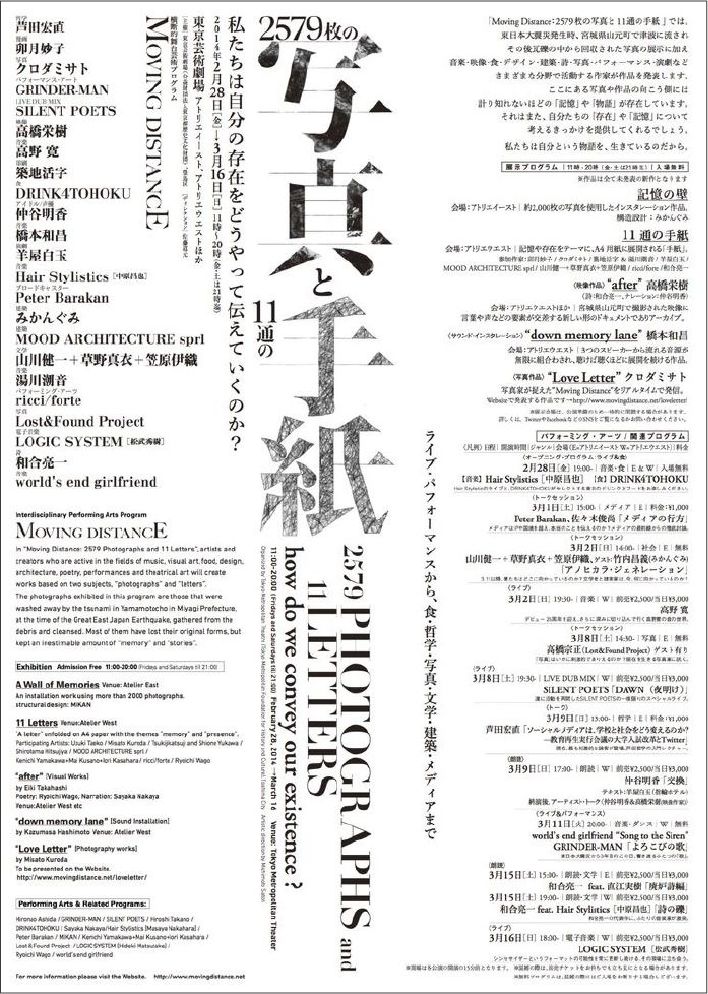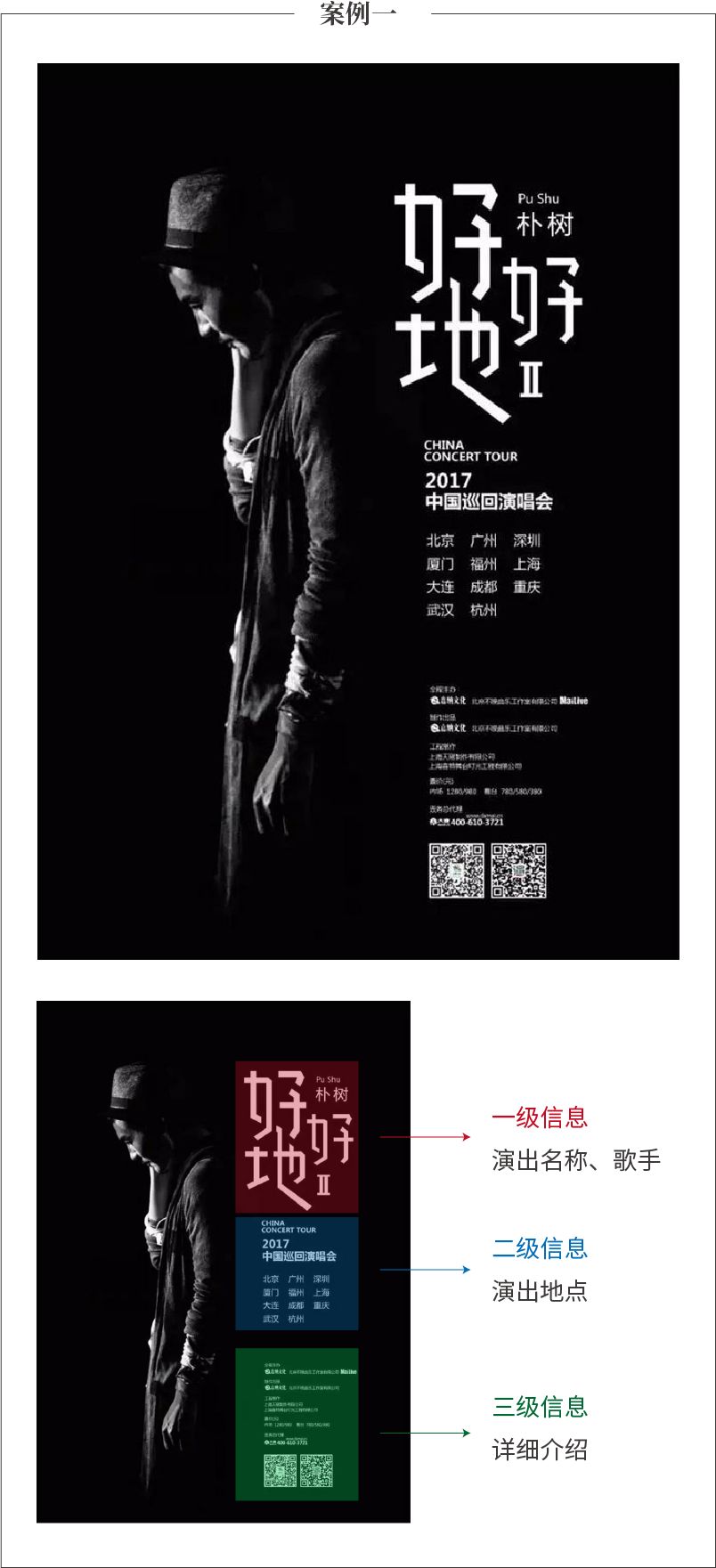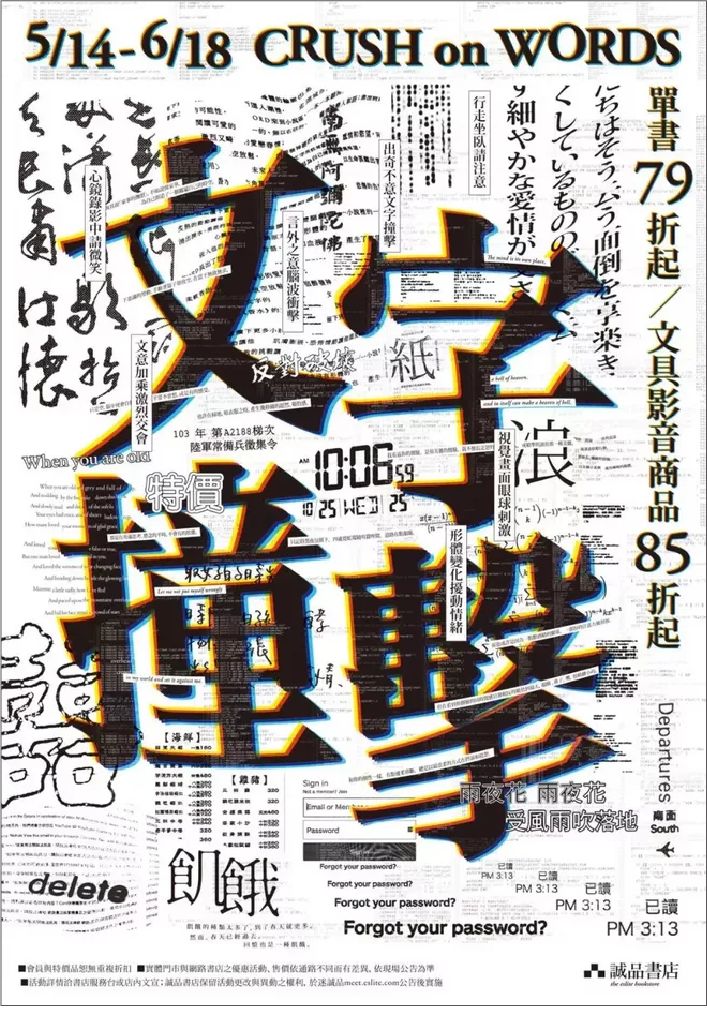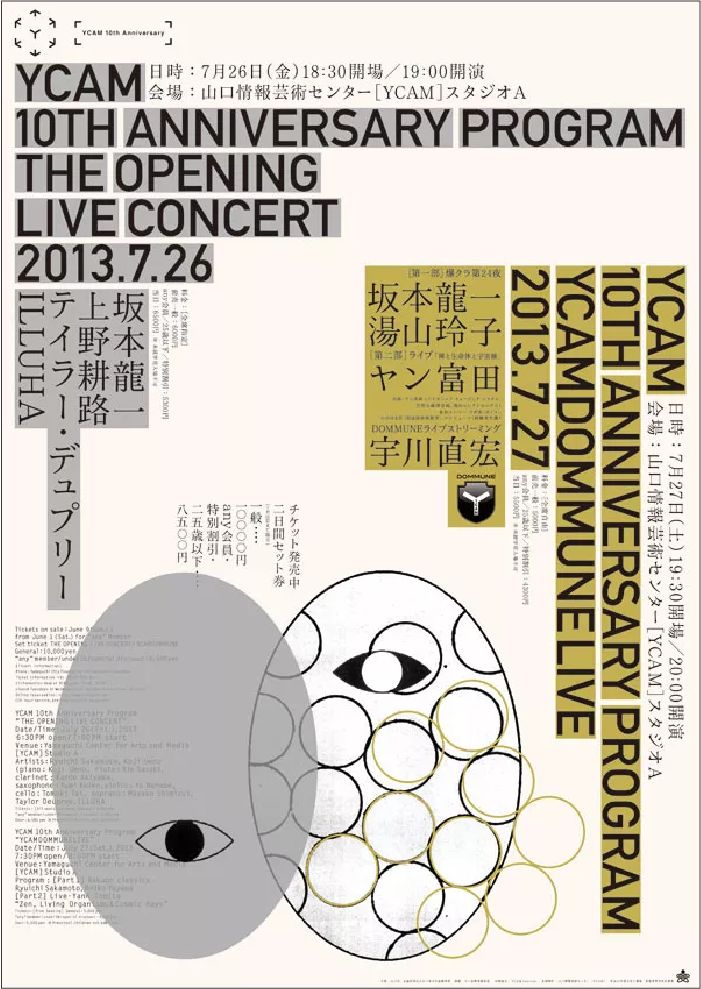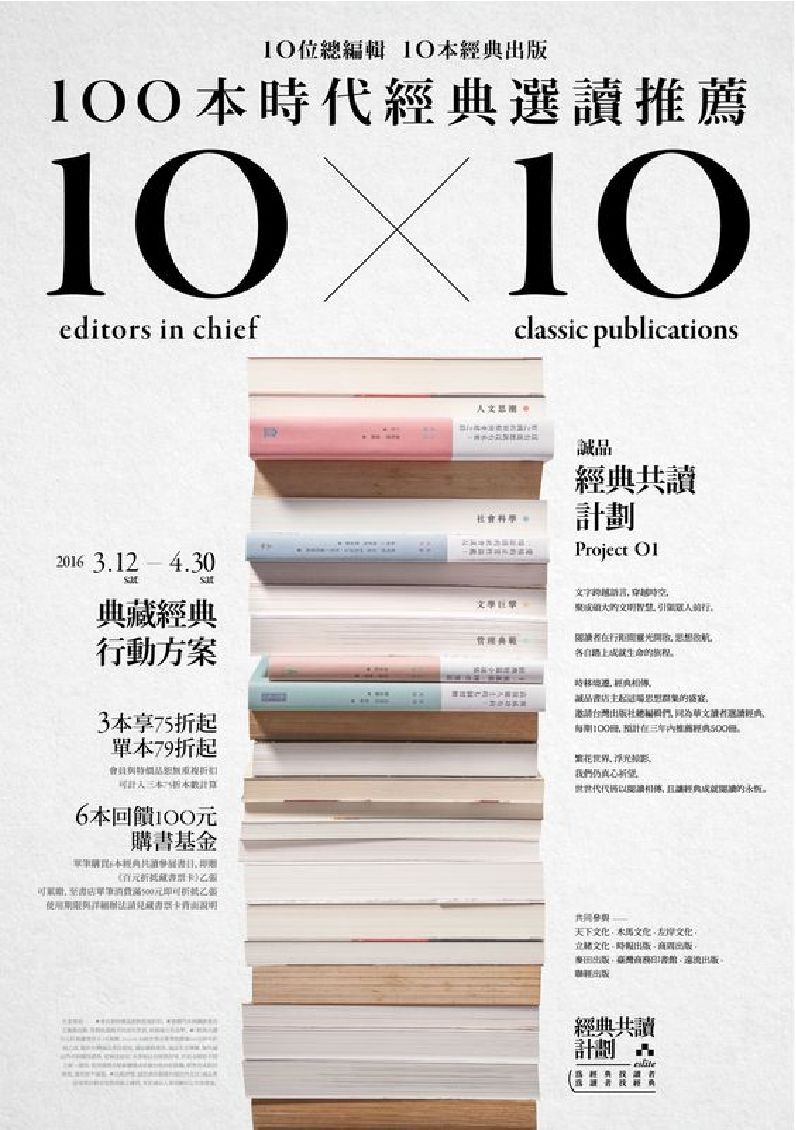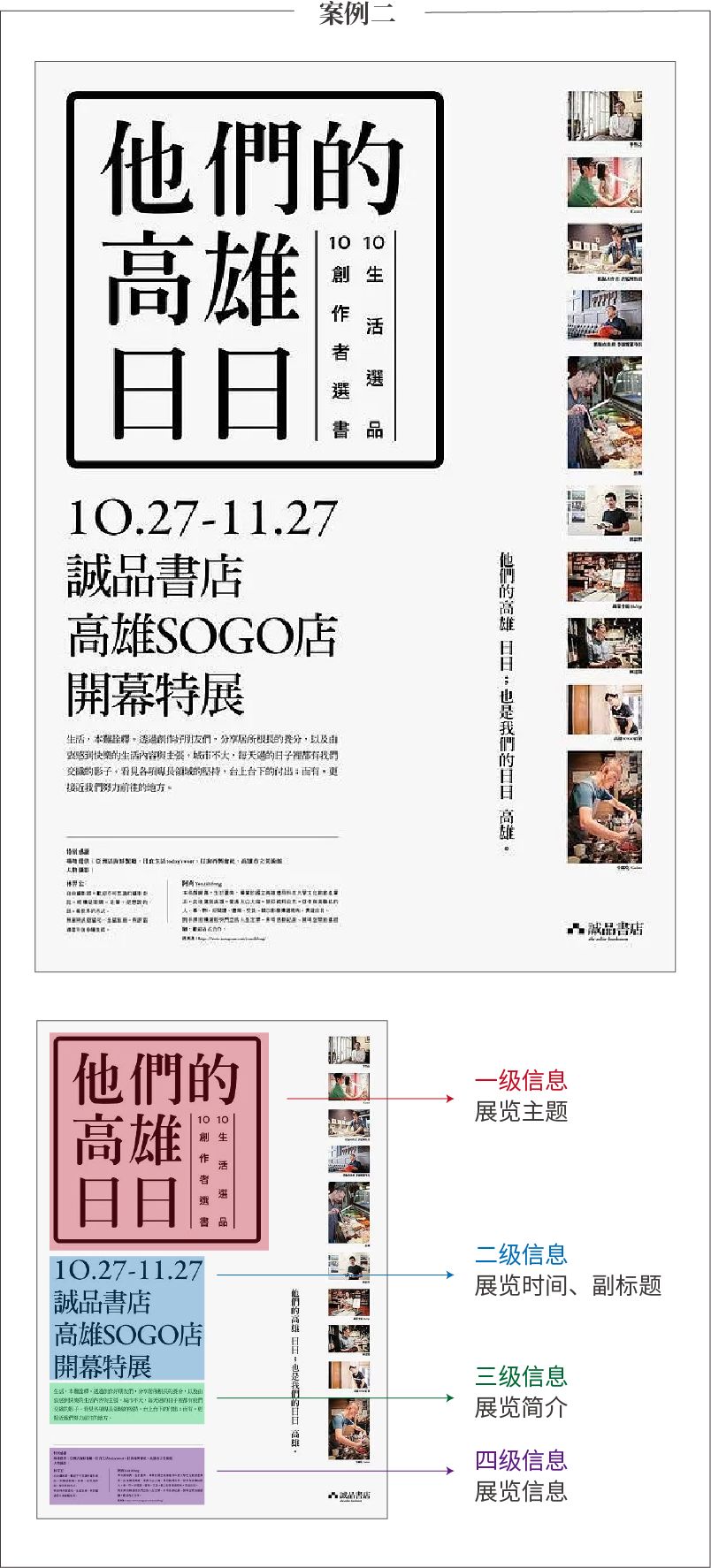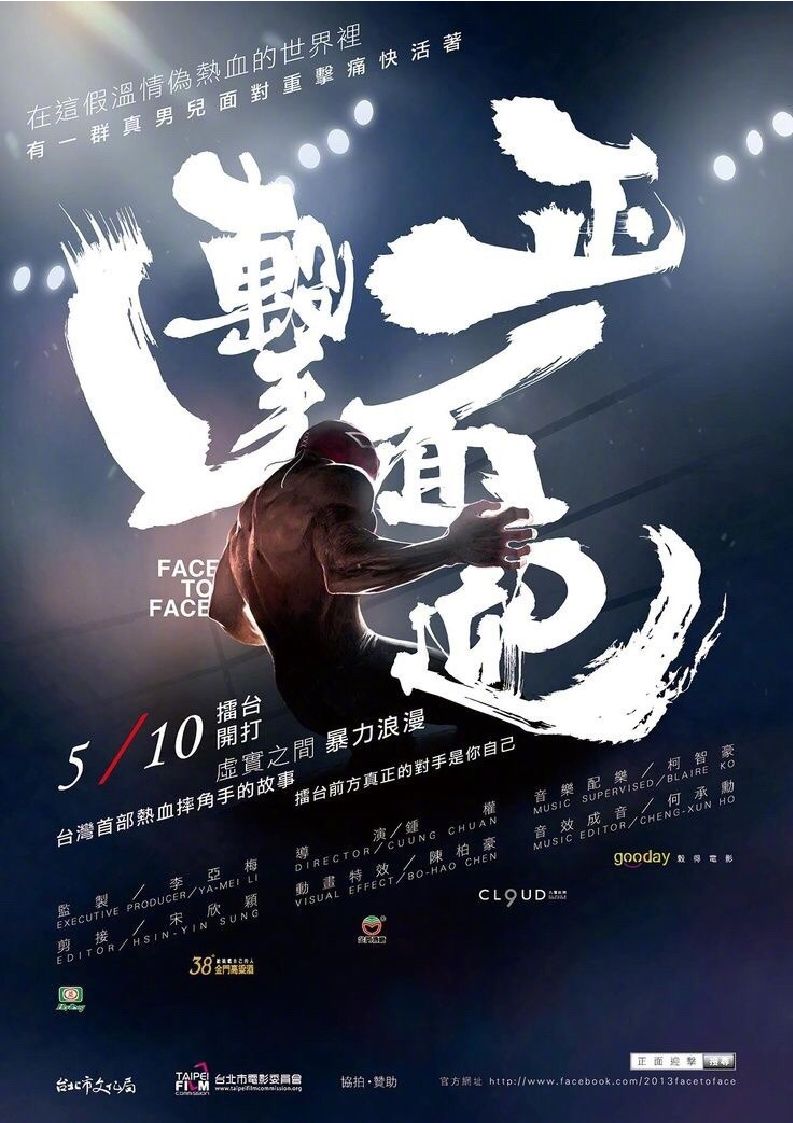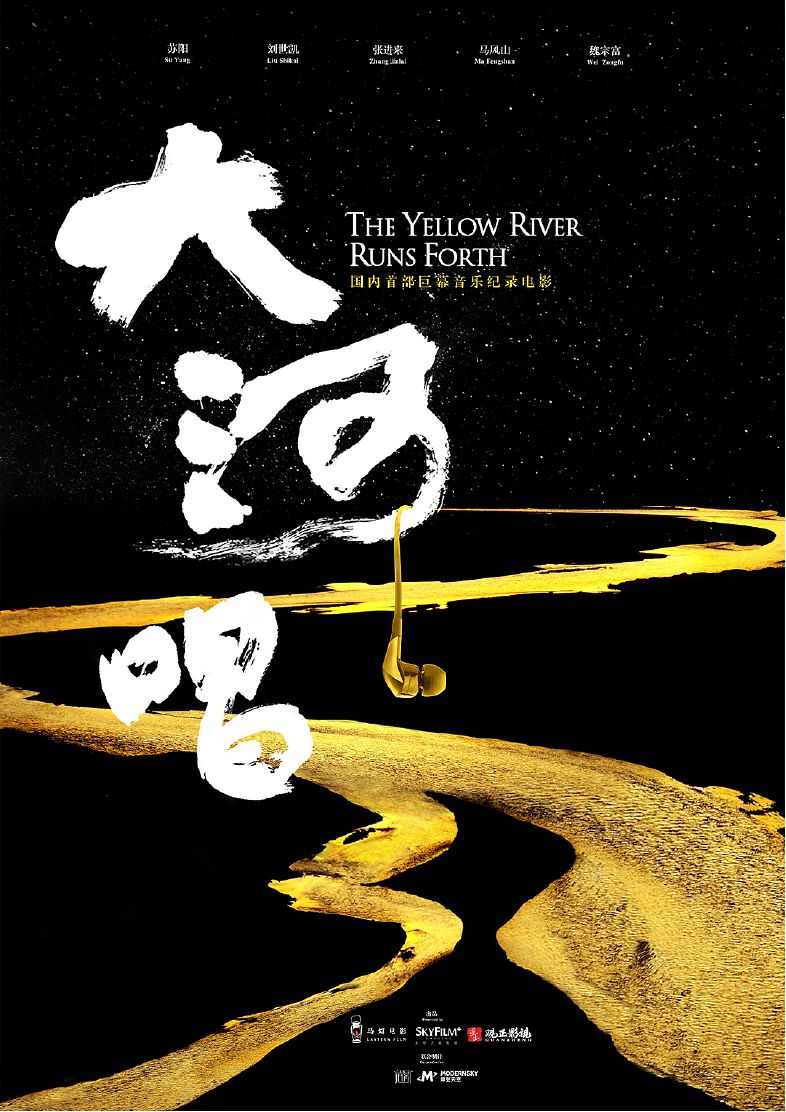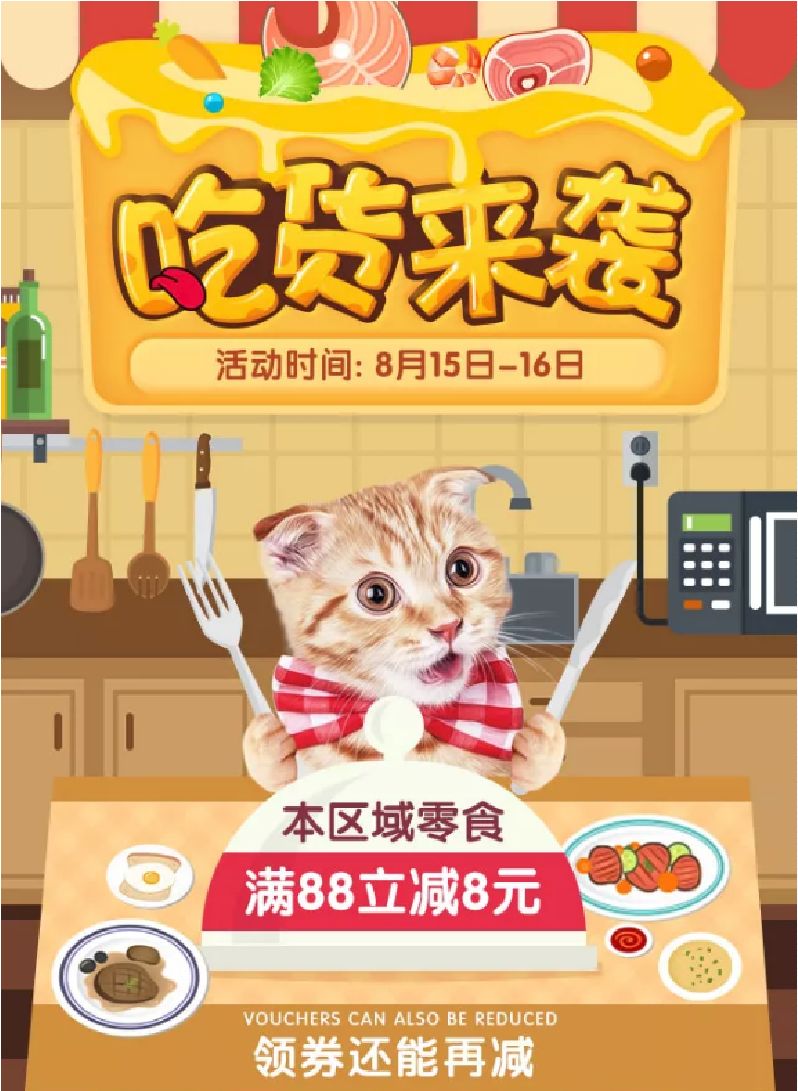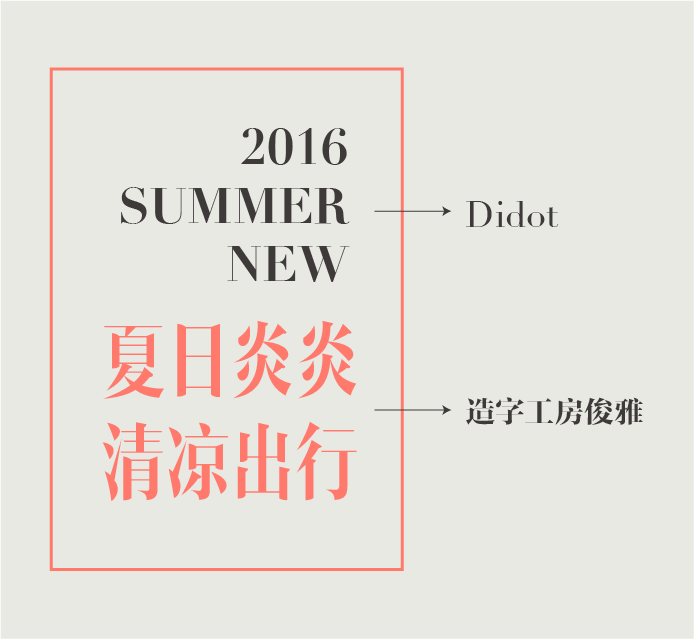
设计中如何搭配字体,快速掌握字体搭配思路
上一期通过“黑体”、“宋体”、“圆体”、“书法体”四大类字体的分析,讲解了各类字体的风格特点和在各种设计案例中的使用效果 ;我们可以根据“目标受众”、“项目调性”、“行业属性”等方式确定字体类型,使字体和版面风格相契合。本期将通过字体搭配三大原则:限制字体数量、建立视觉层次、风格气质的统一,给大家讲解字体搭配的基本技巧。
一个版面中字体的变化不易过多,不论信息量有多少,字体选择控制在二至三种已足以应付画面的需要。即使字体不变,通过改变字体的大小、粗细、颜色或是装饰手法也可达到区分主次、引导读者阅读的目的。字体类型越少,对画面文字信息的编排布局就越容易掌控。
信息量非常大,但只使用一种字体,通过字体大小、粗细对比,和巧妙的编排,很好营造出视觉层次。
整个版面只使用两组字体:英文信息使用粗壮的无衬线字体,并放大强调 ;而日文信息使用较细的衬线体,信息层次可以得到很好区分。
有些项目需要呈现热闹活泼的氛围,或需要非常具有装饰性的设计,必须使用复杂的字体搭配,请保持整体效果是协调的,避免冲突和混乱。
此海报为了营造出热闹丰富的画面感,使用了非常多的字体,形式感很丰富,视觉冲击力很强。但是对于大部分对版面把控力不强的设计师,往往很难做到既丰富又协调 ,所以限制字体数量是使画面达到协调统一的好方法。
为什么要进行字体搭配?一是为了美观,二是为了建立视觉层次。在一个版面中,包含有不同层次的信息内容,需要按主次进行区分,如标题、小标题、内文,每个信息层级也会有重点信息和非重点信息。
在进行字体搭配时需要通过字体的大小、粗细、颜色等方式来配合展现,帮助读者避免视觉上的混乱,同时给版面带来阅读的层次感。
这两个案例虽然只使用了一种字体,但是也可以清晰划分出主次层级。一般来说主体信息可以选择较粗、较大的字体,次要信息使用较细、较小的字体,形成对比,制造视觉流程,引导受众阅读信息,使版面的层次更丰富。
使字体搭配协调的一个基本原则就是选择气质相近的字体。不同造型特点形成各种风格特征的字体,它们所传达出的情感也不相同。有的字体气质庄重,有的字体散发出古典气息,有的给人以现代时尚感,有的字体注重信息传递,而有的注重精神象征。
使用同一字族里的字体,是最简单、安全的搭配方法。所谓字族(font family)即字体家族,一款字体下的多个子字体,如思源黑体和思源宋体字族从细到粗共有七款字体,风格协调统一。
使用同一字族里的字体,符合“限制字体数量”的原则;在编排时需要遵循“形成视觉层次”的原则,在进行字体搭配时需要通过字体的大小、粗细、颜色等方式来给版面带来阅读的层次感。
搭配不同的字体时,要注意他们之间的包容性,既要有所区别又要统一和谐。
黑体与宋体的混搭是很常用的一种搭配方式,当感性的宋体遇上理性的黑体,可以形成很好的对比效果。这里需要注意的是尺度的把握,适当的对比能够为版面带来变化丰富的视觉印象,但对比过度也会产生凌乱感。
如下图化妆品广告,选择较细的宋体和较细的黑体搭配,字形相似又形成了微妙的对比,而且两者都有高雅、精致的气质,运用在具有女性特征的化妆品设计中相得益彰。
配不同的字体时,一般主信息选择较宽粗和具有装饰性的字体,以便能快速吸引受众的注意 ;而说明文字适合选择结构清晰,笔画简洁的字体,以方便阅读。如下图选用“华康海报体”作为主标题,既醒目又活泼生动,能很好吸引受众观看;说明文字选用简约可爱的“方正兰亭圆体”,既具有很好的阅读性,也与标题风格相统一。
书法字形的视觉张力很大,笔画变化丰富且非常具有视觉冲击力。作为展示的标题来说非常适用,但是对于小尺寸的说明性文字并不适合,笔画细节会因为尺寸的缩小变得格外复杂。为了解决这个问题,我们通常会搭配同样具有厚重的文化历史感和强烈的人文气息的宋体。
书法字体搭配黑体,硬朗的黑体与柔和的手写体能够产生强烈的对比效果,非常适合标题的文字组合,常使用在具有现代感的画面中。
使用中英文组合排版时,英文尽量不要使用中文自带的字体,因为部分中文字体的英文部分设计的并不够完美,所以尽量使用经典的英文字体效果会好很多。
上方为“微软雅黑”的中英文组合,下方把英文替换为经典的英文字体“Helvetica”,可以看到下方的搭配更精致美观。
现在把英文单独进行对比,注意看“F”、“C”、“L”、“I”等字母,会明显看到“微软雅黑”的英文设计比较粗糙,“Helvetica”更显精致。
上方为“方正风雅宋”的中英文组合,可以看到中英文风格差异比较大;而把英文换为经典的英文时尚字体“Didot”,明显在风格上更统一,也更适合搭配。
案例分析
此案例中文选择“造字工房俊雅”,英文没有选择字体自带的西文,而是选择更经典的时尚英文字体“Didot”,可以很好营造出时尚的氛围。
在中英文搭配中,通常会选择把英文的衬线字体和宋体字对应编排,而把英文的无衬线字体和中文的黑体字对应编排,这样的搭配方式是最简单,最安全的方法,可以较好的形成风格上的统一。
但每种类型的字体也有细微的气质差别,如宋体字形中也会有书写感很重的古典感字形与极具几何特性的现代字形之分。
偏向于印刷和屏显类的“思源宋体”,搭配冷静克制的英文字体“Times New Roman”会更统一。从细节上来说,它们俩之间的衬角修饰感更为接近,在粗细的过渡及对比上,也是较为近似的。
所以在进行设计时,不管是中文与中文还是中英文搭配,都是需要经过仔细分析和不断练习,才能达到和谐统一、层次清晰而美观大方的效果。
总 结
在字体搭配中要遵循三大原则:
1、限制字体数量。不论信息量有多少,字体选择控制在二至三种已足以应付画面的需要;
2、建立视觉层次。在进行字体搭配时需要通过字体的大小、粗细、颜色等方式来配合展现,帮助读者避免视觉上的混乱,同时给版面带来阅读的层次感;
3、风格气质的统一。搭配不同的字体时,要注意他们之间的包容性,既要区别又要统一和谐。
使用中英文组合排版时,英文尽量不要使用中文自带的字体,在中英文搭配时也要遵循以上三个原则。